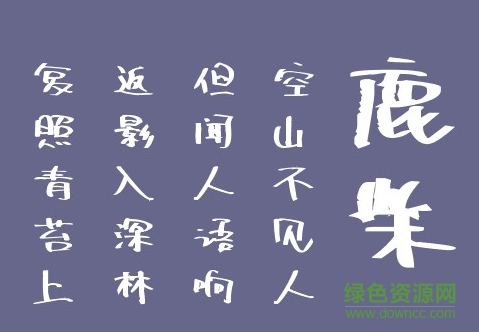
軟件介紹 軟件標簽: 葉根友尚樂體 葉根友 葉根友尚樂體是一款有著柔美大方風格的葉根友字體,適合古詩詞的編輯、詞語的排版,讓你的打印觀看更顯個人魅力,綠色資源網(wǎng)你歡迎大家下載使用!字體安裝將字體文件復制到C:\Windows\Fonts文件夾即可完成安裝(Win7用戶可直接右鍵選擇“安裝”菜單進行安裝)。個人版說明僅限個人單機版使用。重要說明該付費下載字體僅限于個人非商業(yè)用途使用,一切用于商業(yè)用途請務必購買正版授權。(個人非商業(yè)用途是指以個人為單位、非商業(yè)產(chǎn)品運作的方式,運用葉根友字體完成個人作品的展示,包括但不限于個人論文、簡歷等作品的設計)。 軟件截圖 上一張下一張(1 / 1) 安裝詳細截圖 猜你喜歡 葉根友 葉根友 葉根友字體是現(xiàn)代社會中使用最為廣泛的字體,包含葉根友疾風草書、葉根友刀鋒黑草等,現(xiàn)綠色資源網(wǎng)小編整合幾款葉根友字體大全供用戶下載,歡迎到綠色資源網(wǎng)體驗! 查看更多>> 葉根友哲在手寫字體 4.00M/中文/6.0/官方版下載 葉根友離賢行書字體 10.00M/中文/5.7/免費版下載 南構字體合集 50.00M/中文/3.7/共16款下載 南構汪本友行書字體 10.00M/中文/3.3/下載 南構標羽歌士體 10.00M/中文/5.0/免費版下載 南構王天喜行書簡體字體 10.00M/中文/2.1/下載 其他版本下載 標題 大小 更新日期 下載 下載地址 電腦版 葉根友尚樂體個人版 點擊報錯 軟件無法下載或下載后無法使用,請點擊報錯,謝謝! 關閉報錯反饋 請描述您所遇到的錯誤,我們將盡快予以修正,謝謝! *必填項,請輸入內(nèi)容 本類最新 葉根友字體庫打包 共18款 葉根友風帆特色簡體 免費官方版 葉根友哲在手寫字體 官方版 南構村花手寫體ttf版 南構王小花手寫ttf常規(guī) 南構日漫風字體 相關文章 文件正在被另一個人或程序使用無法刪除文件怎么辦? 刪除文件遇到系統(tǒng)提示“無法刪除,文件正被另一個人或程序使用”解決方法 黑莓個人郵箱常見問題及中國移動個人郵件業(yè)務使用問題匯總 Windows7中出現(xiàn)“文件正在被另一個人或程序使用” 黑客為你解答個人安全防范的相關問題 WINDOWS 7的個人文件夾定制 用戶評論 熱門評論 最新評論 發(fā)表評論 查看所有評論(0) 昵稱: 請不要評論無意義或臟話,我們所有評論會有人工審核. 字數(shù): 0/500 (您的評論需要經(jīng)過審核才能顯示)